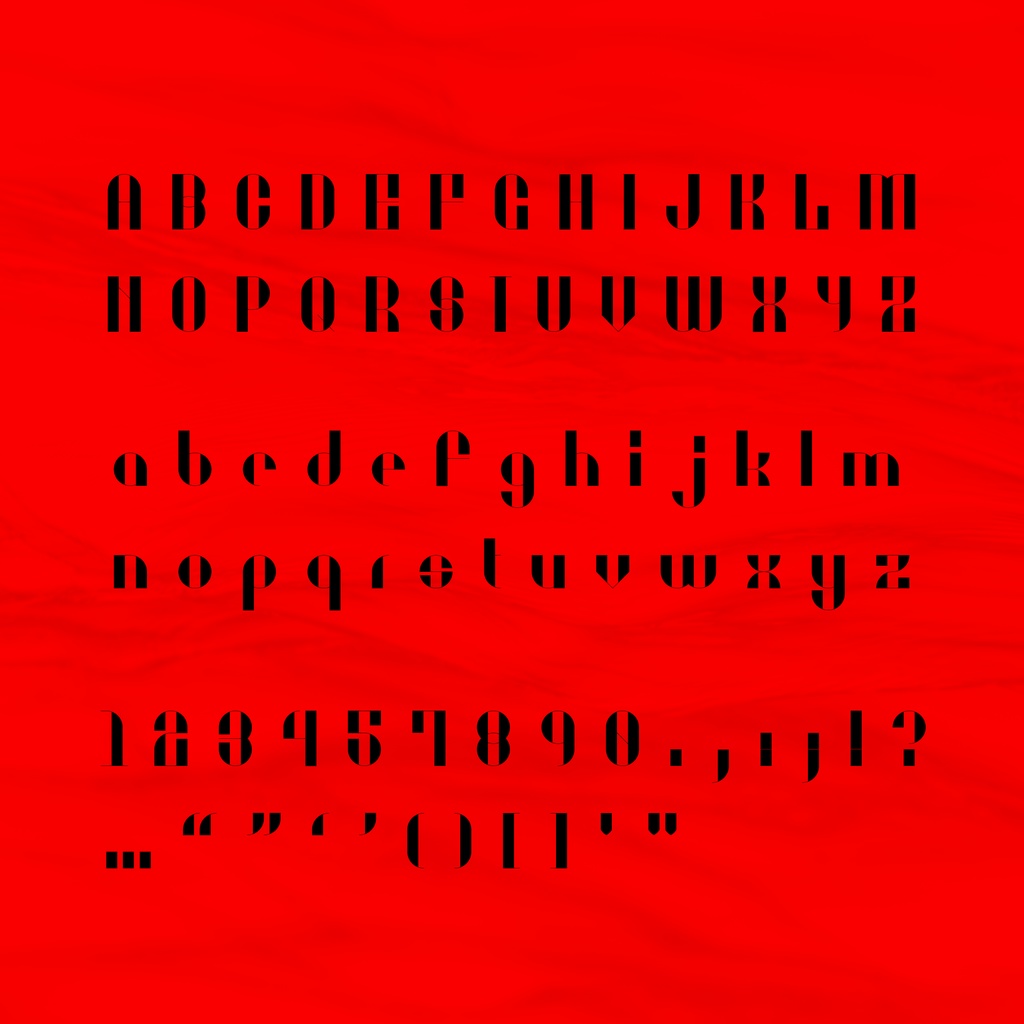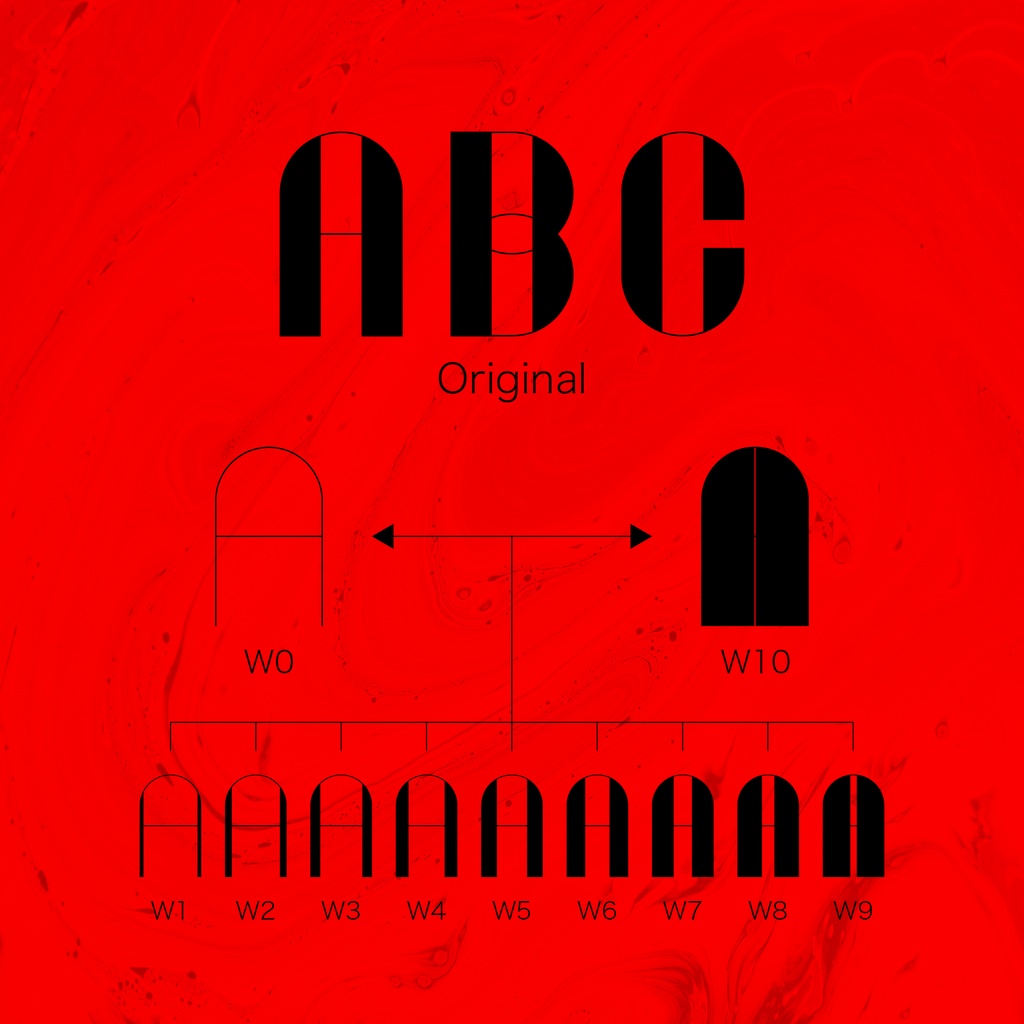
無料【フリーフォント】怒に堕ち·間 Wrath Falling-≬
秩序複写 Order Xeroxing 📢📢📢特記事項📢📢📢 この作品はもともと6日間で完成していたのですが、可変フォントの作り方を工夫して、さらに半月ほどかかりました。 しかし、ソフトウェアの制約上、このフォントを可変フォントにすることができず、現在のバージョンはオプションとして12種類のスタイルしか作ることができない。 📢デザイン説明 すべての垂直ストロークを強調し、他のストロークを弱める。 スタイルごとに異なるプロポーションを自由に選択可能。 📢利用規約 このフォントは無料でダウンロードできる。 個人、商用どちらでも利用可能です。 もしもこのフォントが使用されたら、https://twitter.com/amari_designに教えていただけるとうれしいです! 本素材を使用した作品については、リツイートなどの形で宣伝させていただく場合があります。 フォントのインストール等の技術的なサポートはいたしません。使用して発生したと思われる如何なる問題についても、作者は責任を負わないものとします。 著作権を放棄することはありません。 商標を登録したり、作者であると主張したり、データ自体を販売または再販したりすることは禁じられています。 このコンテンツの最終的な解釈権は作者に帰属します。 内容補充とバージョン更新は製作続けるです。使用する際は最新バージョンにご注意ください。 📢収録內容 怒に堕ち·間/Wrath Falling-≬はラテン文字、数字だけてを含む83文字が含まれています。 ーーーーーーーーーーーー Twitter:https://twitter.com/amari_design Behance:https://www.behance.net/9f45706b ーーーーーーーーーーーー